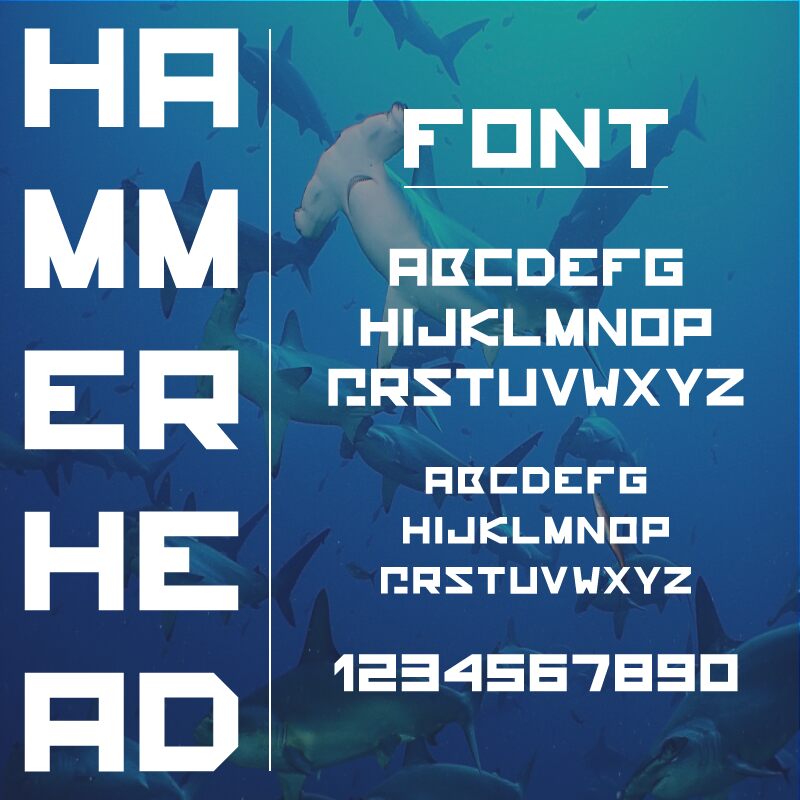
Hammerhead von Davide Lasagni ist eine kostenlose Techno-Display-Schriftart mit einer brutalen, blockartigen Präsenz, die ihrem Namen alle Ehre macht. Breite, quadratische Lettern, enge Punzen und scharfe Innenschnitte verleihen ihr einen mechanisch-industriellen Look, als wäre jedes Glyphe aus Stahl gestanzt. Die Geometrie bleibt sauber und starr, sodass sie selbst in großen Größen kontrolliert und nicht chaotisch wirkt.
Mit Hammerhead wirken deine Überschriften sofort konstruiert und wuchtig. Damit ist diese kostenlose Schrift die ideale Wahl für Spiele-Cover, Sci-Fi-Poster, Tech-Branding, Electronic-Music-Artworks und plakative Event-Flyer. Sie brilliert in Versalschrift mit großzügiger Laufweite. Kombiniere sie für den Fließtext mit einer schlichten, leichten Grotesk oder Neo-Grotesk, damit Hammerhead den Impact liefert, während die ergänzende Schrift für Lesbarkeit sorgt.